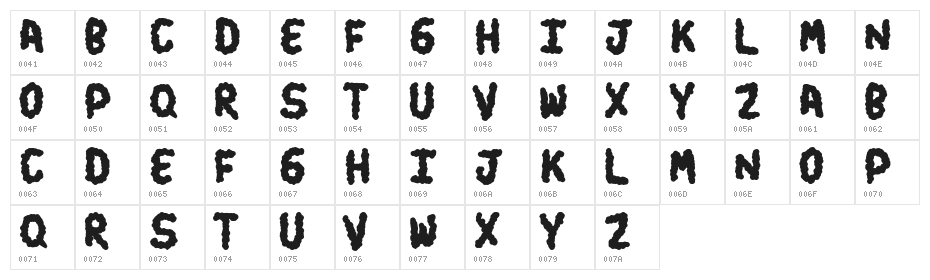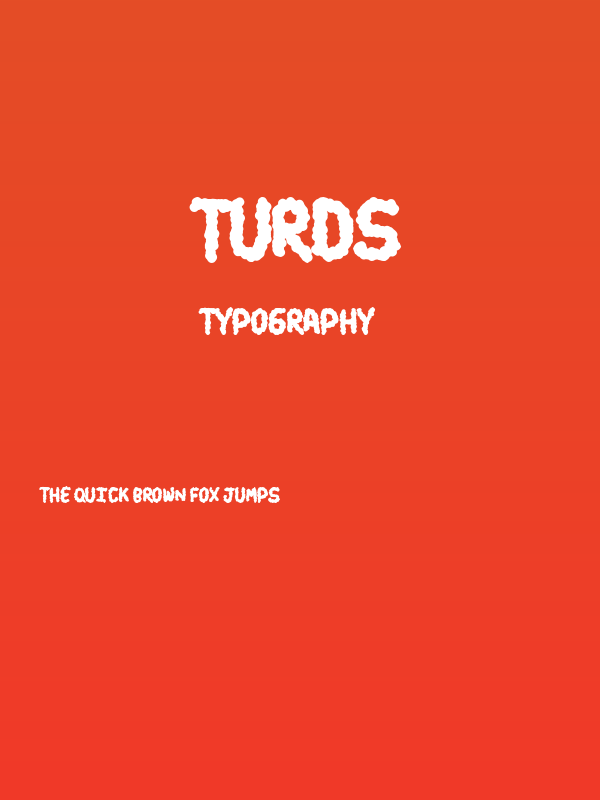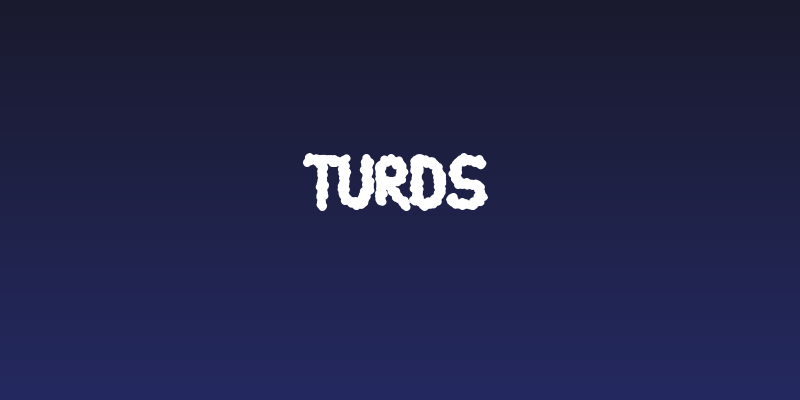
turds Font
| Stile generale | Playful, Modern |
| Caso d'uso | Logos, Headlines, Posters, Invitations |
| Progetti proposti | Ideal for children's books, comic strips, playful branding, party invitations, and any project requiring a fun and informal touch. |